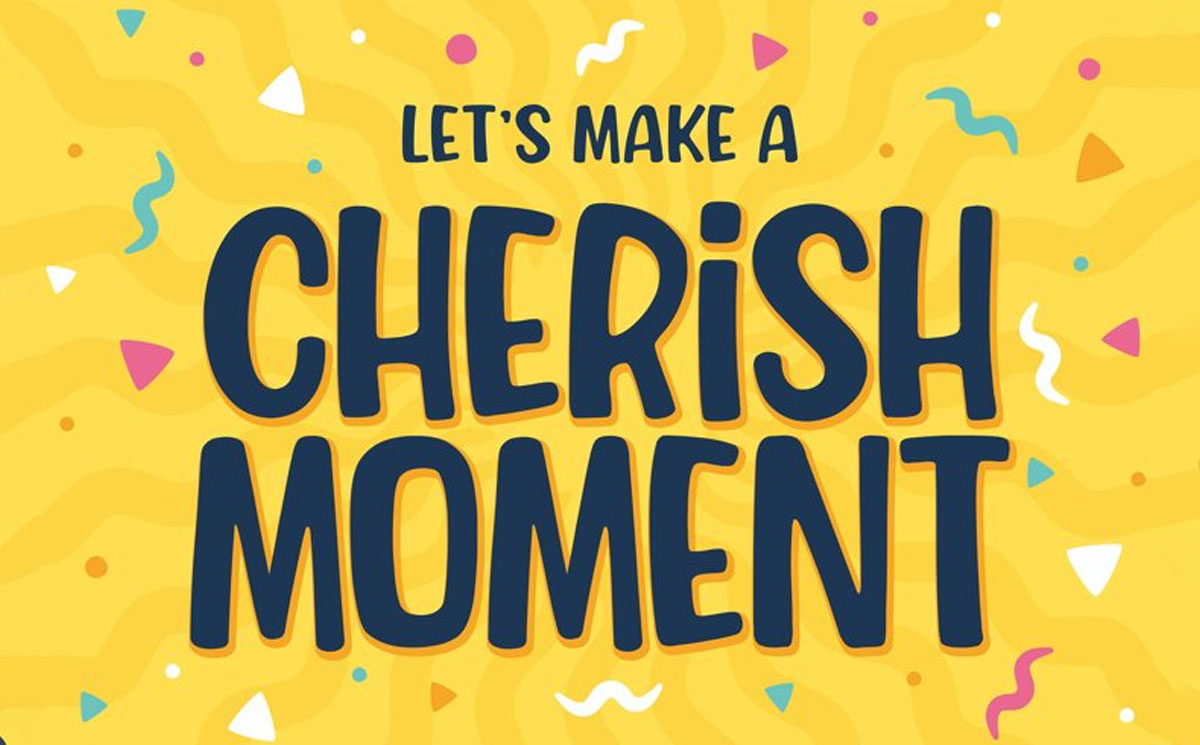
Font chữ hoạt hình vui nhộn SVN Cherish Moment | Phông chữ Việt hóa miễn phí
Nếu bạn đang tìm kiếm một phông chữ mang lại cảm giác tươi vui, dí dỏm và đầy năng lượng cho các sản phẩm thiết kế của mình, thì SVN Cherish Moment chính là sự lựa chọn không thể bỏ qua. Đây là bộ font chữ hoạt hình vui nhộn được Việt hóa trọn bộ, giúp các designer dễ dàng truyền tải thông điệp một cách sinh động, độc đáo và cực kỳ ấn tượng. Hãy cùng trải nghiệm phông chữ Việt hóa miễn phí tuyệt vời này để biến các ý tưởng thiết kế độc đáo của bạn thành hiện thực ngay hôm nay!
Khám phá Font chữ hoạt hình vui nhộn SVN Cherish Moment | Phông chữ Việt hóa miễn phí đỉnh cao cho mọi thiết kế sáng tạo
Trong thế giới thiết kế đồ họa hiện đại, việc lựa chọn font chữ đóng vai trò tiên quyết trong việc định hình cảm xúc của người xem. Những bộ phông chữ truyền thống cứng nhắc đôi khi không thể thể hiện hết sự hồn nhiên, tinh nghịch của các chủ đề dành cho trẻ em, các sự kiện giải trí vui nhộn hay những chiến dịch truyền thông mang phong cách trẻ trung. Nhận thức được nhu cầu đó, bản Việt hóa SVN Cherish Moment ra đời như một làn gió mới, cung cấp giải pháp typographic nét vẽ hoạt hình mượt mà, phá cách nhưng vẫn giữ được độ đọc tốt và sự cân đối hoàn hảo trên mọi chất liệu hiển thị.
1. Phong cách nét chữ hoạt hình phá cách, tự nhiên và giàu cảm xúc
SVN Cherish Moment sở hữu đường nét thiết kế độc đáo với các đường cong bo tròn mềm mại, tạo ấn tượng thân thiện và gần gũi ngay từ cái nhìn đầu tiên. Các chữ cái không tuân theo quy tắc lề lối quá gò bó mà có độ lệch chuẩn nhẹ nhàng, mô phỏng lại nét vẽ tay đầy ngẫu hứng của các họa sĩ truyện tranh tài hoa. Điều này giúp mỗi dòng chữ trở nên có hồn, xóa tan vẻ khô khan thường thấy của các phông chữ gõ văn bản thông thường. Phong cách hoạt hình vui nhộn này rất phù hợp để thu hút sự chú ý của người xem, đặc biệt là đối tượng trẻ em, học sinh và những ai yêu thích sự sáng tạo tự do.
2. Tối ưu hóa 100% tiếng Việt chuẩn Unicode với bộ ký tự đầy đủ
Một trong những điểm cộng lớn nhất của bản SVN Cherish Moment chính là việc được Việt hóa vô cùng chỉn chu và tỉ mỉ. Toàn bộ các dấu thanh tiếng Việt (sắc, huyền, hỏi, ngã, nặng) cùng các ký tự đặc trưng như ê, ô, ơ, ư, đ… đều được tinh chỉnh khoảng cách (kerning) và vị trí một cách hài hòa. Bạn sẽ không gặp phải hiện tượng lỗi font, mất dấu hay các ký tự bị biến dạng khi gõ tiếng Việt có dấu trên bất kỳ phần mềm đồ họa nào. Sự hoàn thiện này giúp các designer tiết kiệm hàng giờ đồng hồ chỉnh sửa thủ công, đảm bảo tiến độ công việc mượt mà và chuyên nghiệp nhất.
3. Ứng dụng linh hoạt trên nhiều ấn phẩm thiết kế từ online đến in ấn
Không chỉ giới hạn trong một khuôn khổ nhất định, phông chữ hoạt hình vui nhộn SVN Cherish Moment tỏ ra cực kỳ linh hoạt trong nhiều bối cảnh sử dụng khác nhau. Bạn có thể ứng dụng bộ font này để thiết kế bìa sách thiếu nhi, truyện tranh, bao bì sản phẩm đồ chơi, nhãn dán sticker, áo thun gia đình, hoặc tiêu đề banner cho các sự kiện sinh nhật, trung thu, Giáng sinh. Bên cạnh đó, trên nền tảng số, SVN Cherish Moment cũng thể hiện xuất sắc khi làm hình thu nhỏ (thumbnail) YouTube, hình ảnh bài đăng mạng xã hội (Facebook, Instagram, TikTok), giúp nội dung của bạn nổi bật giữa vô vàn thông tin khác.
Gợi ý phối màu và kết hợp Font SVN Cherish Moment trong thiết kế
Để phát huy tối đa vẻ đẹp của phông chữ hoạt hình vui nhộn SVN Cherish Moment, việc áp dụng các nguyên lý phối màu và sắp xếp bố cục là vô cùng quan trọng. Dưới đây là một số mẹo nhỏ giúp bản thiết kế của bạn thêm phần lôi cuốn:</p>
• Sử dụng bảng màu tươi sáng, tương phản cao: Các gam màu như vàng nắng, cam pastel, xanh lục bảo, đỏ dâu hay xanh pastel sẽ làm nổi bật nét tinh nghịch của font chữ. Bạn có thể tạo hiệu ứng chữ viền (stroke) hoặc đổ bóng (drop shadow) nhiều lớp để dòng chữ trông nổi 3D sống động hơn.
• Kết hợp với phông chữ phụ nét đơn giản: Vì SVN Cherish Moment là một font dạng display (tiêu đề) có tính trang trí cao, bạn nên kết hợp nó với các phông chữ Sans-serif tròn trịa, nét sạch sẽ cho các đoạn văn bản dài (body text) để giữ sự cân bằng và dễ đọc.
• Chèn thêm các icon hoạt hình và đường nét trang trí: Thêm vào thiết kế những biểu tượng ngôi sao, tia sét, đám mây hay nốt nhạc bo tròn sẽ làm phong phú thêm không gian thị giác xung quanh dòng tiêu đề SVN Cherish Moment.